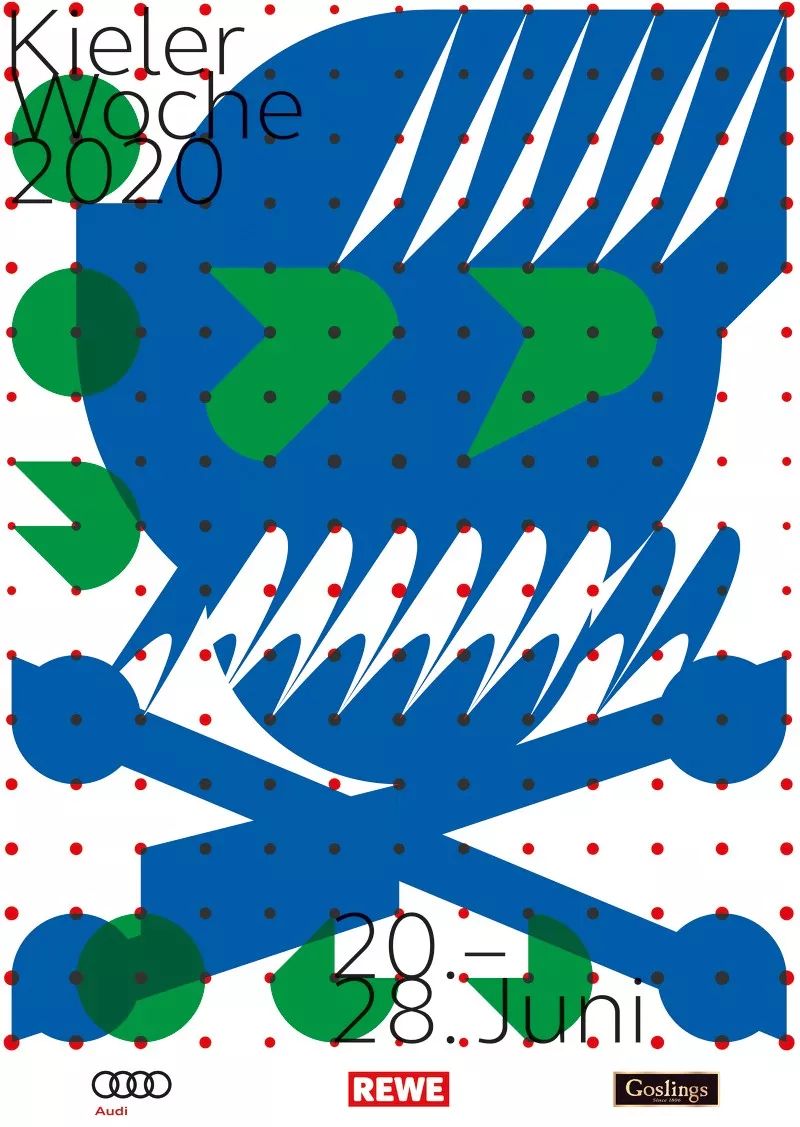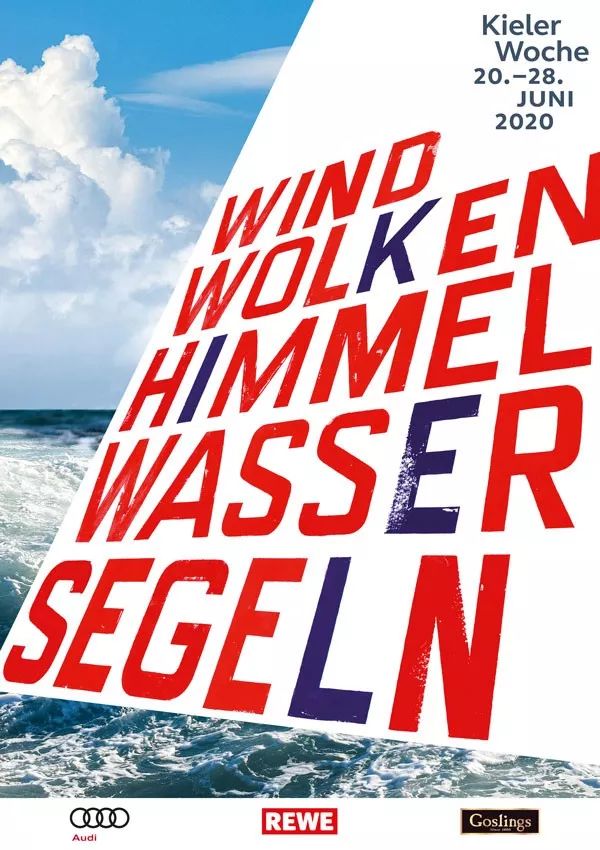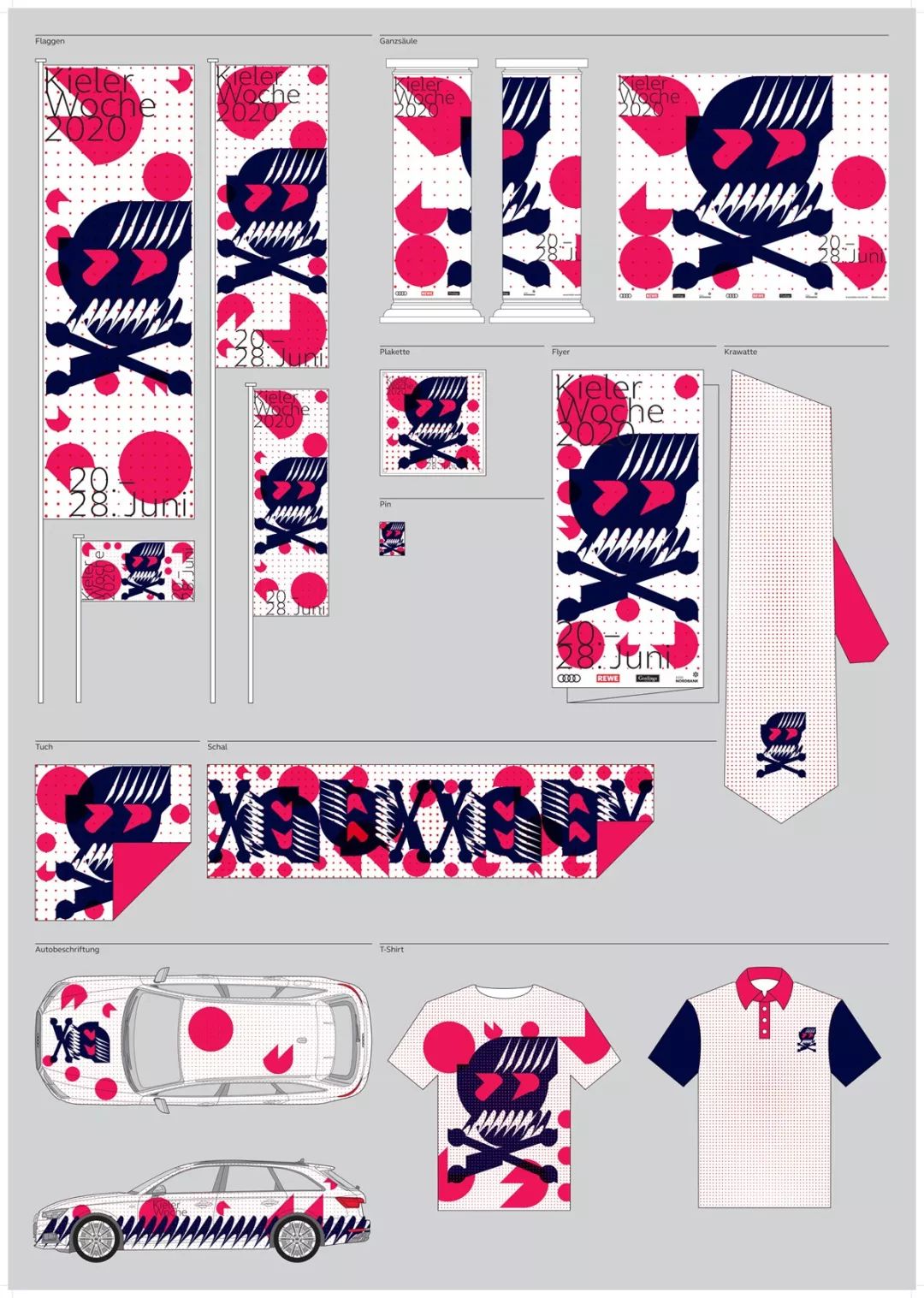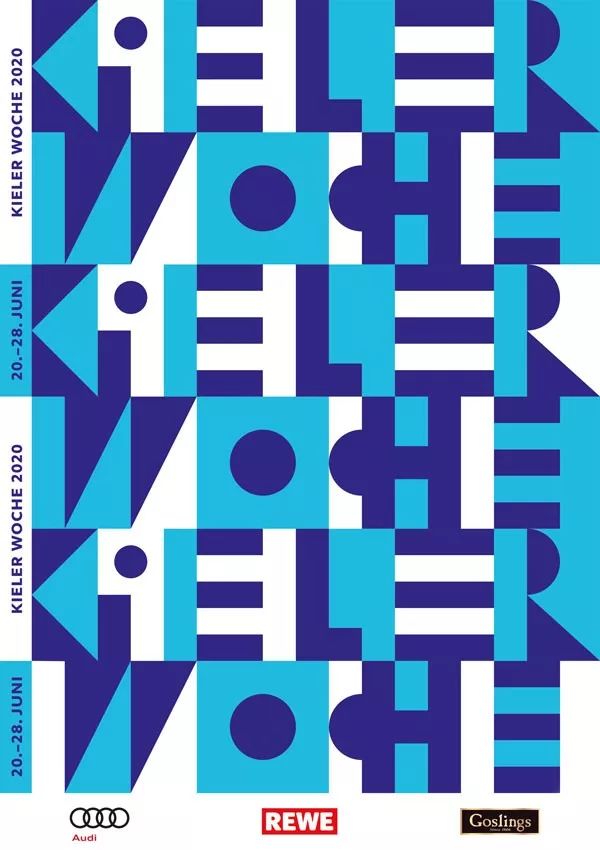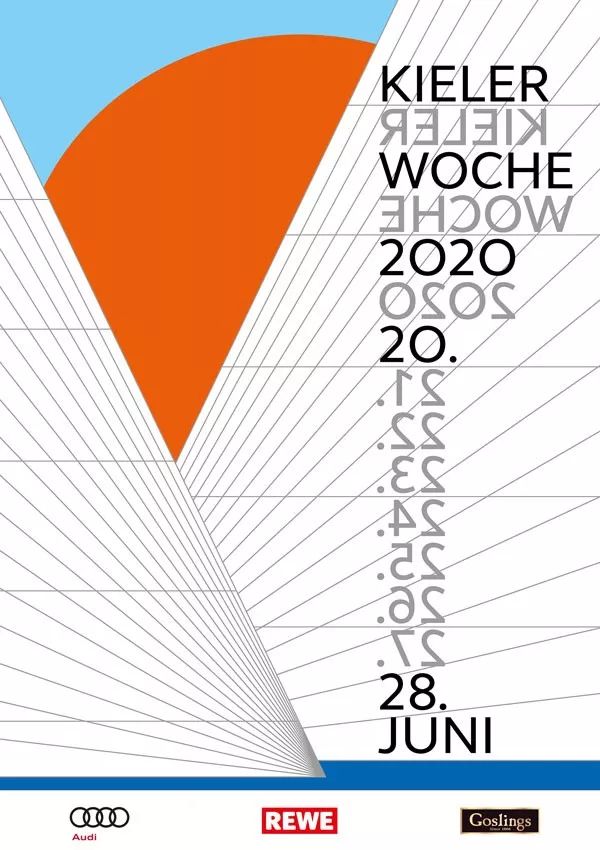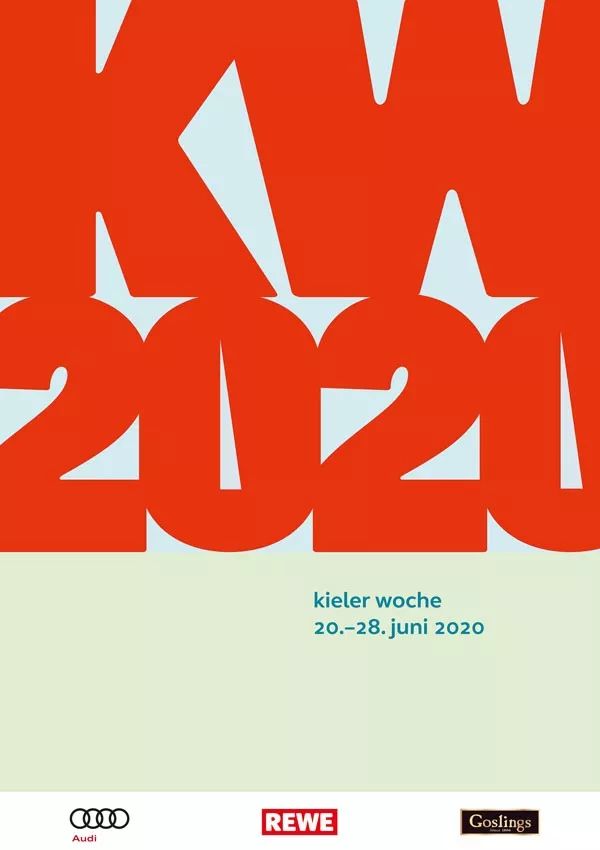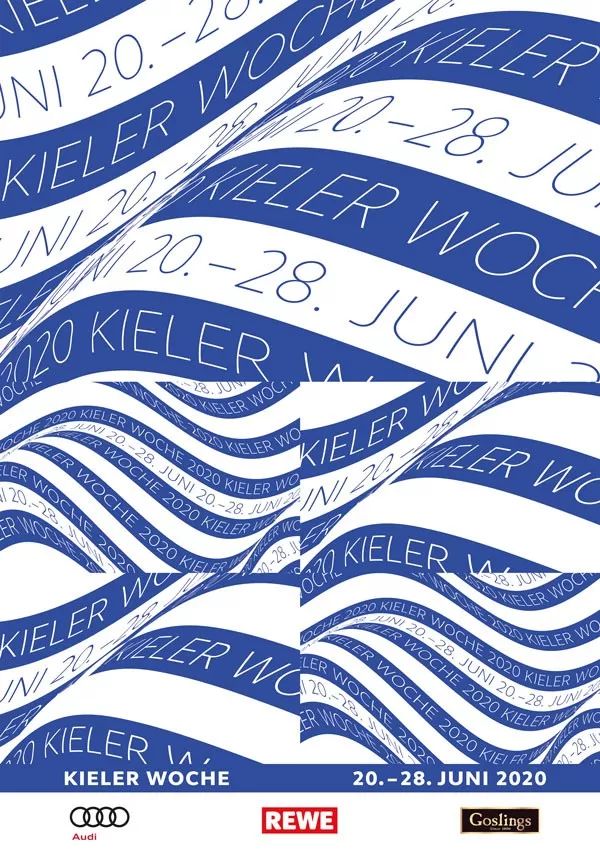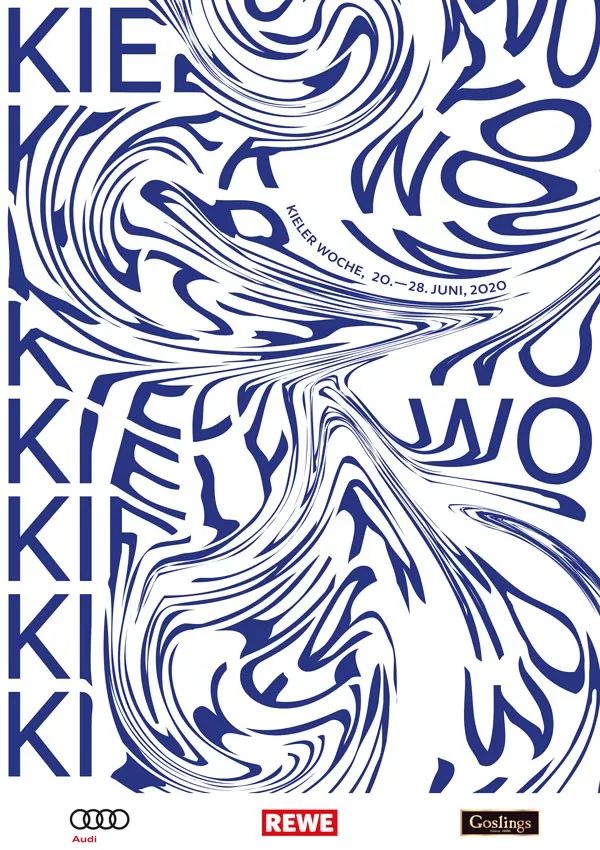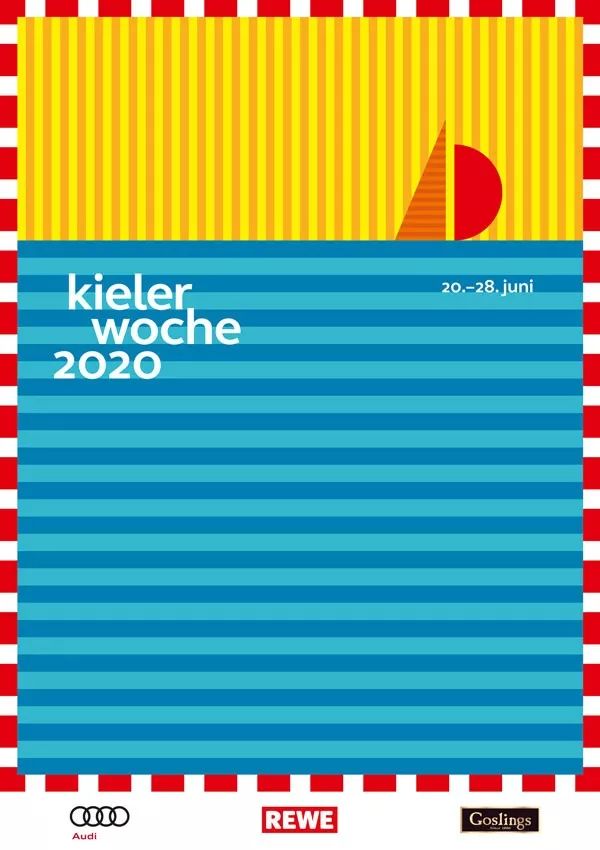
2020 德国基尔周帆船赛海报竞赛获奖公布
2020基尔周帆船赛官方海报
每年一度的 Kieler 周对其形象设计具有最高的标准:自1959年以来,著名的设计师们被邀请参加此活动的形象设计。被邀请即是一种荣誉。
此设计大赛享有非常高的国际声望,特别是因为许多方案被授予国际奖项。
自1948年以来,创作出了超过70幅海报为世界独一无二的,因此也是对平面设计的历史发展的一种反射。
2020年的设计
为了2020年的设计,来自国际上5家设计工作室,总共贡献出了13幅海报。在9月3号,评委们评选出了来自瑞士巴塞尔的设计师 Jiri Oplatek 的海报作品。
评委们说:
获奖的海报呈现出了幽默感及富有情绪。具有冒险精神及放松和自由的状态,是 Kieler 周的特征。不同的层级中增添出几何的形状,呈现出细节丰富的形态塑造玩法。这样的玩法创造出丰富的联想空间,为 Kiele 周作为夏日节日以及帆船比赛的特点进行了很好的结合。
评审团成员
评委会由4位专业评委,4位项目评委以及1位来自 Kiel 的民众作为评委组成。
其中专业评委为来自 Karlsruh 设计团队的 Andrew Goldstein,柏林设计师 Ariane Spanier,上届的冠军 Daniel Wiesmann 以及 Kieler 活动周办公室主席 Philipp Dornberger。
所有的参赛作品均被展出
从9月5日至9月27日共3周的时间所有的参赛作品将在市政厅展出。在此您可以将自己以评委的角度选出您最喜欢的设计。
设计师:Jiri Oplatek
Jiri Oplatek
Jiri Oplatek 出生于 Brno。毕业于巴塞尔设计学院,2000 – 2003年在‹Meissner & Mangold› 任职设计师。自2003与 Thomas Bircher 和 Roland John 联合成立 ‹Claudiabasel, Grafik + Interaktion› 设计工作室至今。曾今作为客座讲师在 Karlsruhe设计院校/ZKM 任教。自2012年任教于巴塞尔设计艺术院校的视觉传达专业的本科与研究生。
基尔周帆船赛主视觉方案延展部分
其他设计师及其设计
Anna Berkenbusch
曾在杜塞尔多夫学习视觉传达,毕业后曾在柏林和伦敦两地的 Meta Design 工作。自1982年她曾为“Denk Neu”(Communication Agency)的管理合伙人。于1987年在柏林成立了自己的工作室 Anna B.。自1989年以来她开始从事教育工作,自2003年她作为 Burg Giebichenstein Kunsthochschule Halle 艺术院校的教授。除此之外她也是(德国)国内外评审委员会成员以及(德国)科学理事会和大学认证的顾问。
她的工作室主要从事于电影海报设计以及活动的配套物料设计,书籍,手册,形象设计以及邮票设计。Anna Berkenbusch 及她的工作室 Anna B. 获得诸多国内及国际的表彰。
基尔周帆船赛海报方案
Anna Haas
Anna Haas 作为视觉设计师自2011年在苏黎世经营自己的工作室。她曾在卢塞恩学习插画以及在荷兰 Arnhem 学习平面设计。
如今她作为书籍设计师,海报艺术家及插画师,工作范围主要涉及国内外的文化项目。她作为瑞士插画协会的联合创始人及自2014年以来作为本协会主席。
2017年她发起创立一个非盈利的独立书店介绍 APP:“Book Cities”。
她的作品获得过诸多奖项,如瑞士设计奖,瑞士最美的书籍设计奖,以及连续2次获得布尔诺国际平面设计双年展。2016年她获得布尔诺第27届国际平面设计双年展大奖。
自2014年任教于卢塞恩。
基尔周帆船赛海报方案
Slawek Michalt
Slawek Michalt 作为设计师生活工作在柏林。自2007年,他以及他的工作室从事于艺术,文化,服装及体育行业的设计。
在设计工作之余,他活跃在国内及国际的教育行业,如柏林艺术大学,中国美术学院(杭州)。
Slawek Michalt 的字体海报在国内及国际都享有盛誉。
基尔周帆船赛海报方案
Rimini Berlin
Rimini Berlin 的联合创始人: Franziska Morlok, Jenny Hasselbach
Rimini Berlin 作为设计工作室自2007年以来主要为文化类领域的印刷品,数码,影像及空间项目提供设计服务。概念性,实验性的方法构成了项目的基础。与多学科网络合作是 Rimini Berlin 的特点。
通信媒体的战略和跨媒体设计是他们项核心竞争力之一。其中一个重点便是出版。诸多书籍曾获得优秀字体排印设计奖。
此外她们也活跃在艺术设计教育领域。
基尔周帆船赛海报方案
近年历届
基尔周帆船赛
官方海报
2019年 / 设计师:Daniel Wiesmann
2018年 / 设计师:Verena Panholzer
2017年 / 设计师:Götz Gramlich
2016年 / 设计师:Stan Hema
2015年 / 设计师:Zwölf
2014年 / 设计师:Thomas und Martin Poschauko
2013年 / 设计师:Jens Müller und Karen Weiland
2012年 / 设计师:Ariane Spanier
2011年 / 设计师:Melk Imboden
2010年 / 设计师:Andrew & Jeffrey Goldstein
2009年 / 设计师:Prof. Henning Wagenbreth
2008年 / 设计师:Peter Zizka
2007年 / 设计师:Markus Dreßen
2006年 / 设计师:Prof. Klaus Hesse
2005年 / 设计师:Detlef Fiedler
2004年 / 设计师:Bernd Kuchenbeiser
2003年 / 设计师:Clemens Schedler
2002年 / 设计师:Prof. Fons M. Hickmann
2001年 / 设计师:Uli Braun
2000年 / 设计师:Anja Kühn